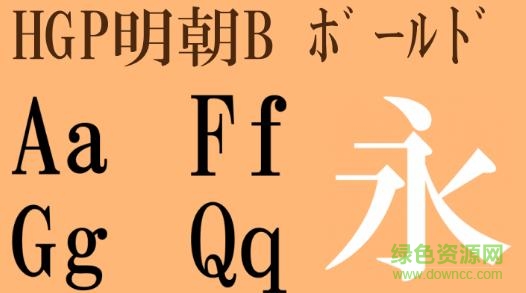
hgp明朝b
hgp明朝b字體是一款美觀大氣的高品質(zhì)日文宋體字體,橫豎比例精致,輪廓清晰,字面大小勻稱,特別適用于各類期刊雜志的正文排版,需要的朋友快來(lái)下載吧!
明朝體的由來(lái)
宋體字在明朝時(shí)傳入日本,因而日本稱之為“明體”或“明朝體”,在電腦漢字字體設(shè)計(jì)的最初,日本率先設(shè)計(jì)了明朝體,后來(lái)傳入韓國(guó)、中國(guó)臺(tái)灣,所以兩地也有明朝體的叫法。
hgp明朝b字體特征
這款字體的筆畫(huà)端正均勻,筆形清秀、舒展,結(jié)構(gòu)寬博,在屏幕應(yīng)用中有良好的表現(xiàn)。